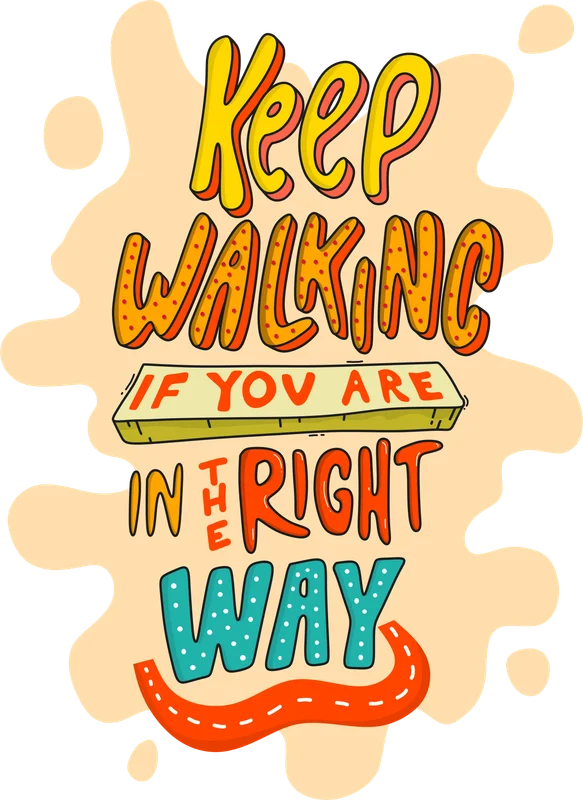
Thông điệp "Keep Walking" đầy cảm hứng, font chữ độc đáo
Thông điệp "Keep Walking" đầy cảm hứng, font chữ độc đáo — Thiết kế typography độc đáo với thông điệp "Keep Walking If You Are In The Right Way" truyền cảm hứng. Phù hợp in áo thun, túi tote, sticker.
Trong hình có: chữ viết, thông điệp, đường đi
Phong cách: cartoon · Cảm giác: khac
Tông màu chủ đạo: vàng kim, cam, xanh ngọc